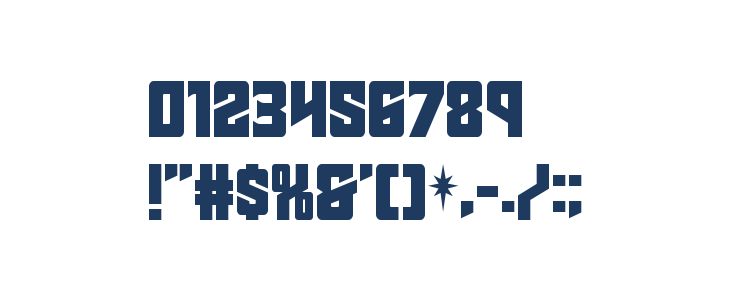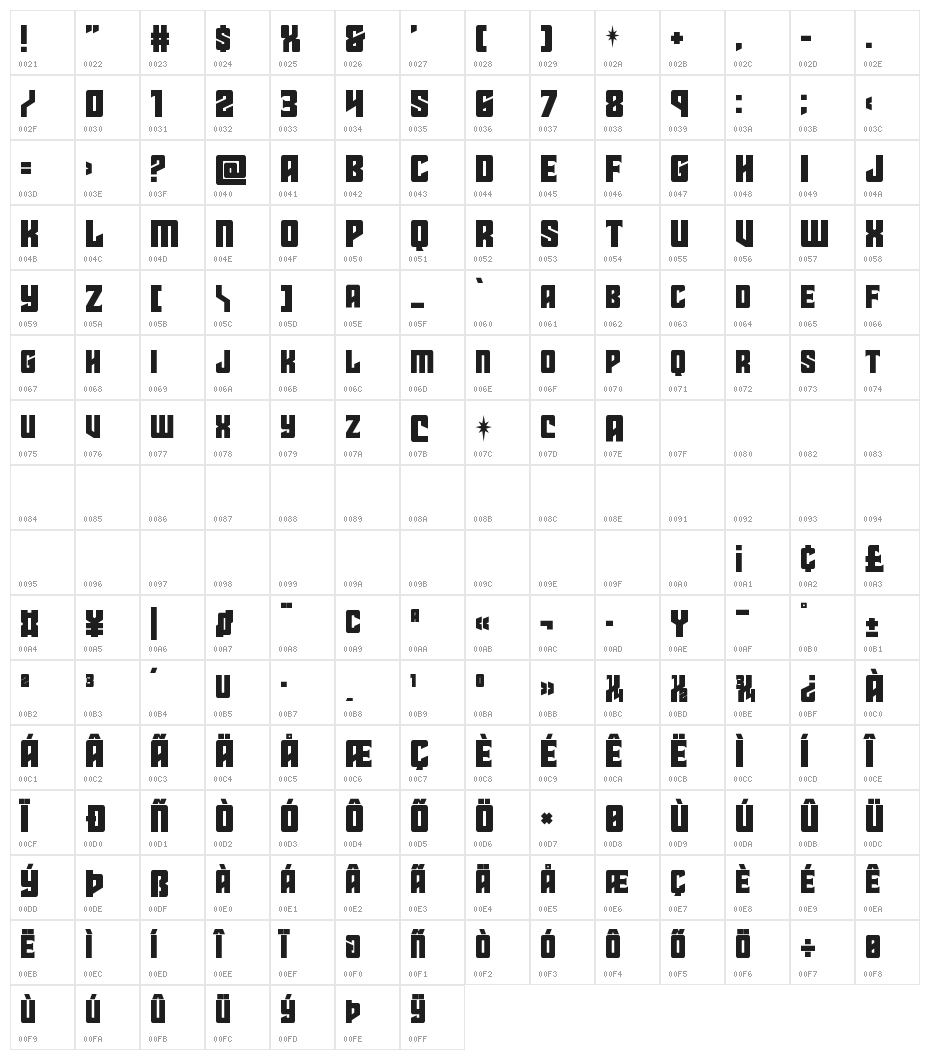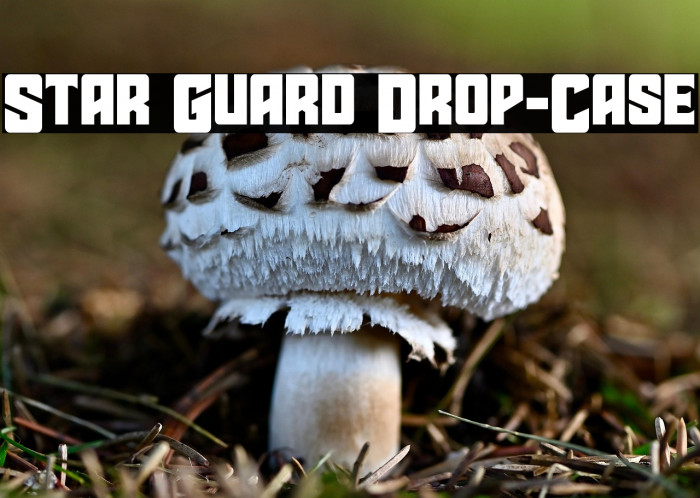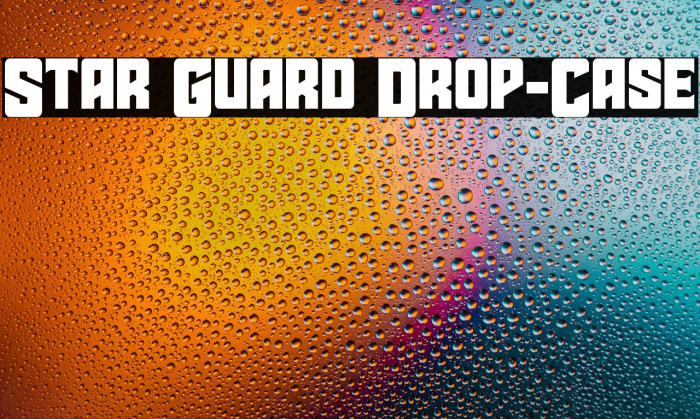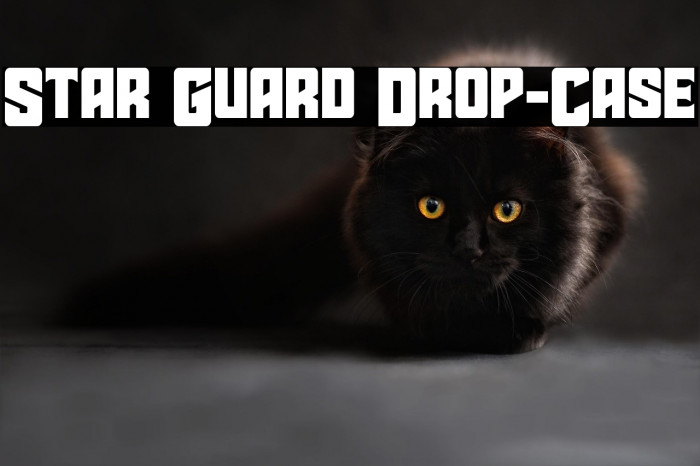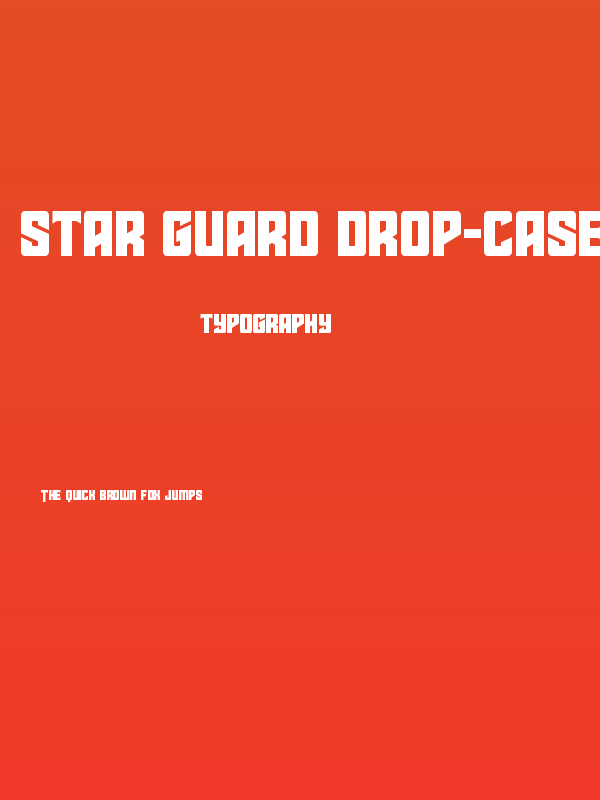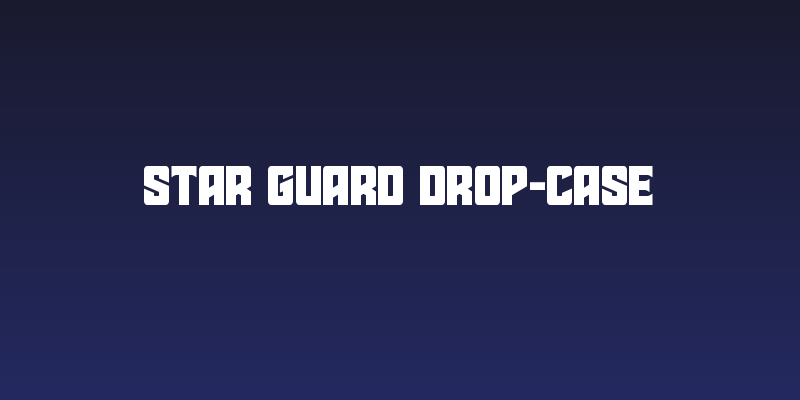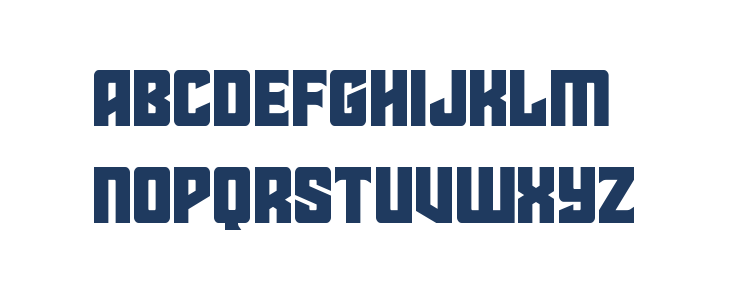
Star Guard Drop-Case Font
✎ Futuristic
| श्रेणियाँ | Futuristic |
| कंट्रास्ट | High |
| उपयोग का मामला | Headlines, Logos |
| सुझाए गए प्रोजेक्ट | Ideal for sci-fi themed posters, video game titles, branding for tech companies, and any project needing a modern, bold statement. |